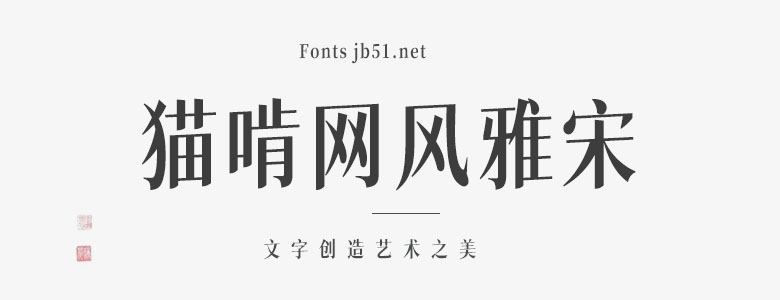
貓啃網(wǎng)風(fēng)雅宋字體是基于獅尾四季春改造獲得的,通過(guò)程序壓縮字體寬度,并把字體向上拔高,只有一個(gè)字重,采用獅尾四季春SC-Bold,字體支持免費(fèi)自由商用,不需要付費(fèi)、知會(huì)或標(biāo)明作者,也可以自由改造成其它字體,改造后的字體也必須同樣授權(quán)公開。
貓啃網(wǎng)風(fēng)雅宋是貓啃網(wǎng)網(wǎng)友@新愚公利用業(yè)余的時(shí)間把獅尾四季春通過(guò)程序進(jìn)行改造,壓縮字體寬度,并把字體向上拔高,有點(diǎn)類似仿宋字形。貓啃網(wǎng)風(fēng)雅宋只有一個(gè)字重,采用獅尾四季春SC-Bold。原字體的一些襯線還依然保留。修復(fù)過(guò)程中發(fā)現(xiàn)這些字體基本上用不上,所以沒(méi)有進(jìn)行修復(fù),所以有興趣使用的網(wǎng)友如發(fā)現(xiàn)常用字體還有襯線存在的請(qǐng)告知,一定時(shí)間內(nèi)會(huì)修復(fù)。